99+ Back to School font Việt hóa đẹp, miễn phí, ấn tượng
Back to school font là lựa chọn quen thuộc khi thiết kế banner, poster, thiệp mời hoặc bài đăng mùa tựu trường. Những font chữ này thường có nét vui nhộn, gần gũi và dễ tạo cảm giác học đường. Bài viết dưới đây tổng hợp nhiều font chữ mùa tựu trường, font Việt hóa và font viết tay đẹp để bạn dễ chọn theo từng nhu cầu.
Back to school font phù hợp cho poster, banner và thiết kế lớp học. Nhóm font này thường vui nhộn, dễ nhìn và tạo không khí tựu trường rõ ràng.
Back to School font là lựa chọn không thể thiếu trong mùa tựu trường năm 2026. Những bộ font này không chỉ giúp thiết kế trở nên bắt mắt hơn mà còn mang lại cảm giác gần gũi. Dưới đây là những mẫu font chữ mùa tựu trường đang được sử dụng rộng rãi nhất hiện nay.
Font này là lựa chọn không thể thiếu cho các thiết kế học đường đúng nghĩa. Với nét chữ tròn đều, dễ đọc và hơi nghiêng nhẹ, mang lại cảm giác gần gũi như nét bút của học sinh trên vở ô ly. Đây là kiểu font lý tưởng cho các bài giảng PowerPoint, banner trường học hay poster truyền cảm hứng học tập.
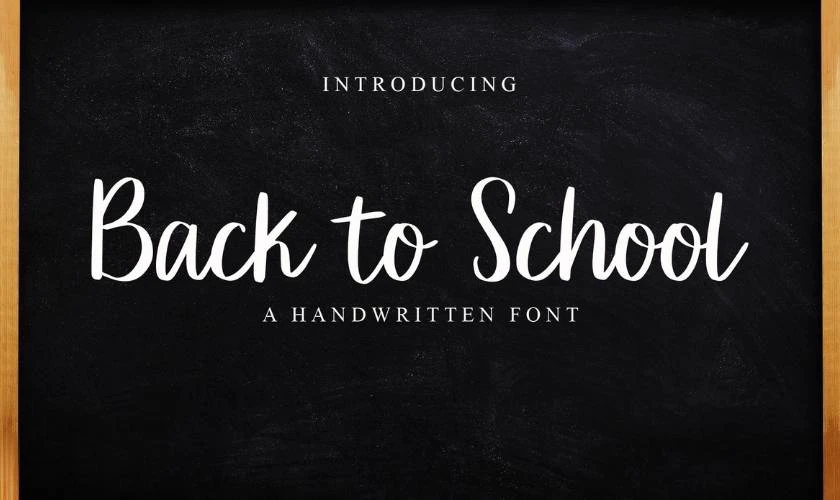
Nếu bạn muốn tìm một font mang hơi hướng retro và có tính học thuật hơn. CF Back to School là cái tên rất đáng cân nhắc. Nét chữ gọn, rõ, độ dày vừa phải giúp font này dễ dàng xuất hiện trên mọi thiết kế. Từ sách hướng dẫn, infographic lớp học cho đến thiệp mời khai giảng.
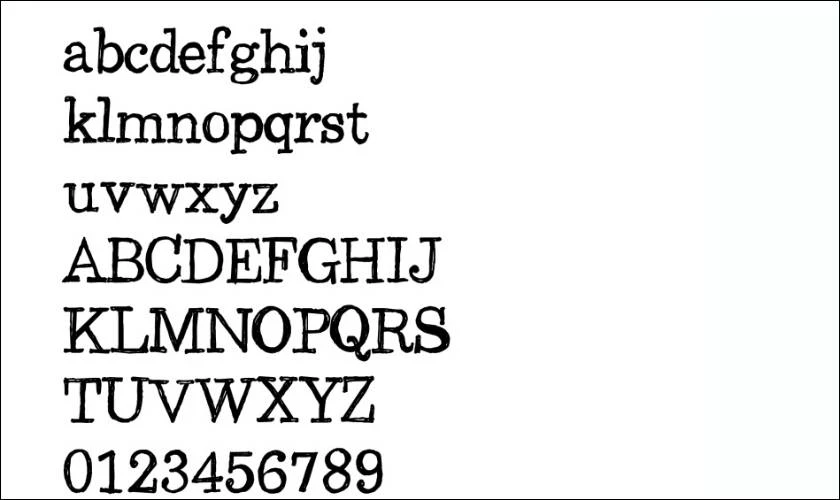
Không khí vui tươi, đáng yêu và dễ thương là điều mà font chữ PW mang đến. Nét chữ mềm mại, độ cong hài hòa khiến font này phù hợp với cấp mầm non, tiểu học. Nếu bạn đang làm sổ tay, bảng tên lớp hay thiệp handmade, font này là lựa chọn hoàn hảo.
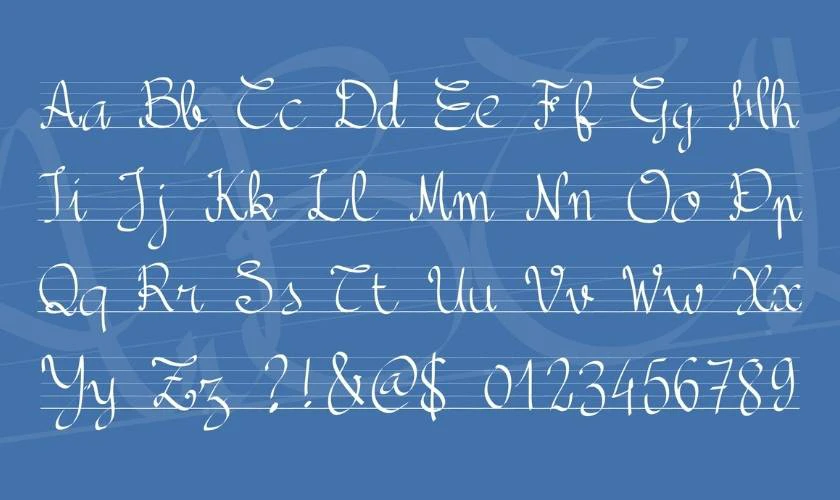
Imagex có kiểu dáng cổ điển nhưng vẫn giữ được tính hiện đại nhờ đường nét chắc khỏe, dứt khoát. Font chữ mùa tựu trường của Imagex thường được dùng cho tiêu đề lớn. Ví dụ như backdrop, banner hoặc áp phích sự kiện. Độ tương phản cao giúp font nổi bật mà vẫn giữ được sự chuyên nghiệp.
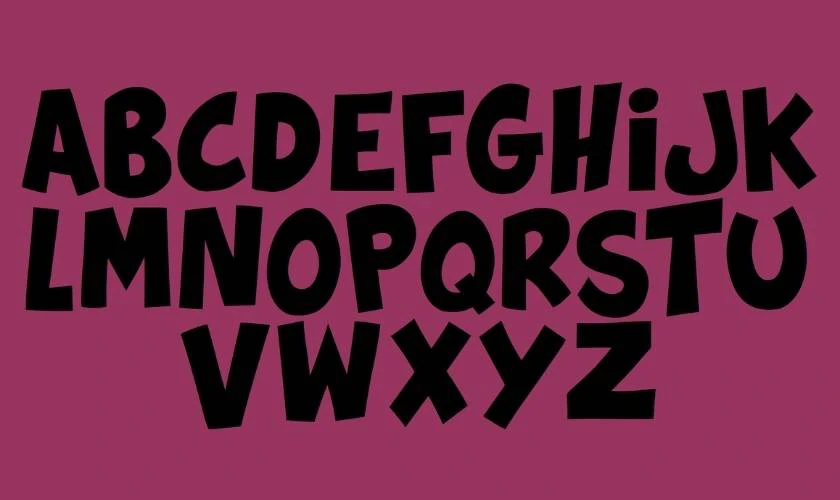
Đặc biết font khá “dễ tính” khi phối màu và dùng được cả trên nền tối lẫn nền sáng.
Phong cách tự do và có phần tinh nghịch. Đây là font rất được ưa chuộng trong các hoạt động ngoại khóa. Font này cực kỳ hợp cho các thiết kế mang tinh thần “nổi loạn nhẹ”. Chẳng hạn như áo lớp, sổ truyền thống hoặc poster sự kiện trường.
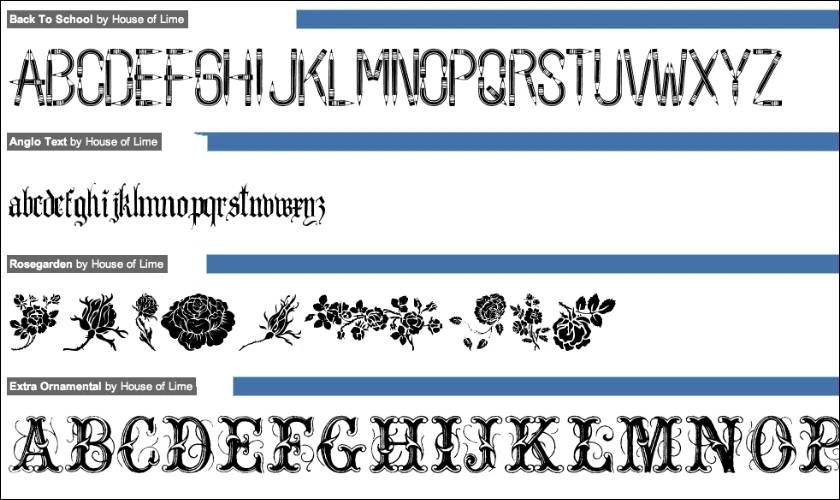
Dù có kiểu dáng hơi phá cách, House of Lime vẫn giữ được tính dễ đọc, rất thân thiện với người dùng. Bạn hoàn toàn có thể phối hợp font này cùng icon hoặc minh họa doodle để tăng phần sinh động.
School Mania là font mang phong cách học đường vui nhộn với các nét chữ đậm. Font dễ nhận diện, phù hợp với thiết kế cần sự nổi bật.
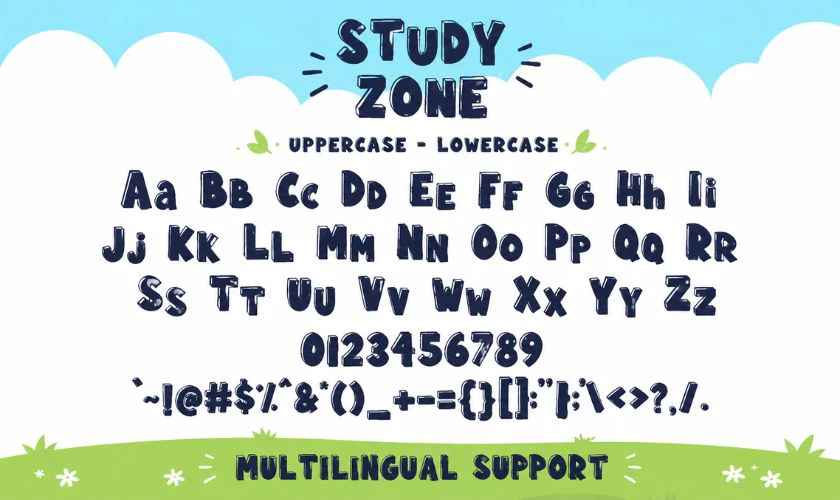
Bạn có thể dùng font này cho tiêu đề poster, banner khai giảng hoặc chương trình chào năm học mới. Font hoạt động tốt khi đặt ở vị trí trung tâm.
Sweetie Pie là font chữ viết tay với nét uốn lượn dịu dàng, thích hợp cho thiết kế dành cho học sinh nữ hoặc chủ đề trường học nhẹ nhàng, lãng mạn. Font có cả phiên bản thường và nghiêng.
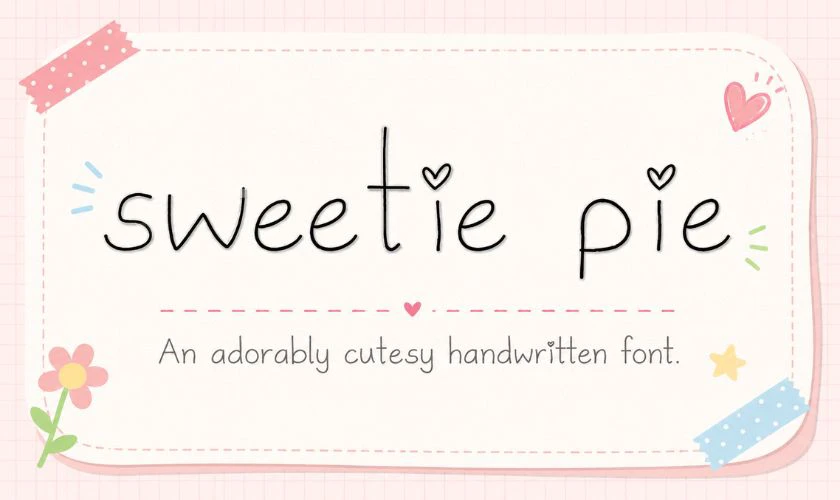
Màu sắc pastel kết hợp cùng Sweetie Pie sẽ cho ra bộ thiết kế hoàn chỉnh, phù hợp cho sticker vở bài tập, nhãn vở học sinh hay thẻ tên lớp học.
Pencil Pete mô phỏng nét vẽ bằng bút chì, tạo cảm giác rất gần gũi. Font gợi nhớ đến vở học sinh, bảng viết và các hoạt động lớp học.
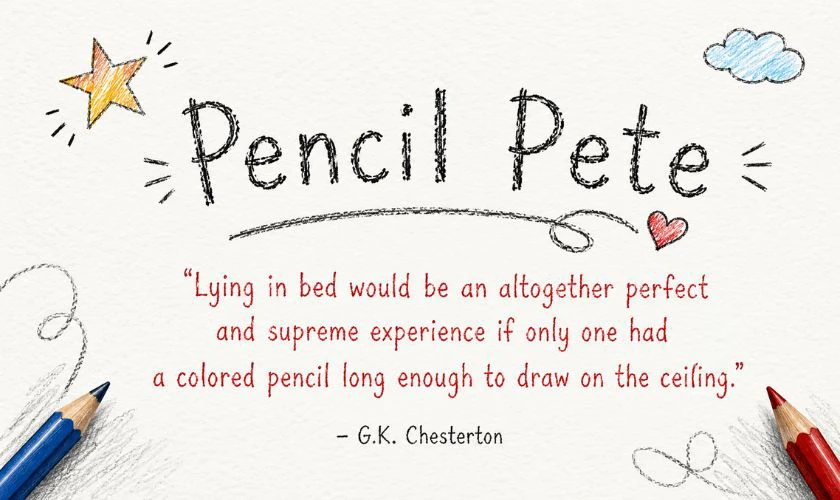
Đây là lựa chọn phù hợp cho thiết kế sáng tạo dành cho học sinh. Bạn có thể dùng Pencil Pete cho flashcard, poster học tập hoặc ảnh minh họa giáo dục.
School Days có phong cách trẻ trung, thân thiện và dễ đọc. Font phù hợp với nhiều nội dung học đường, từ thông báo đến bài đăng chào năm học.
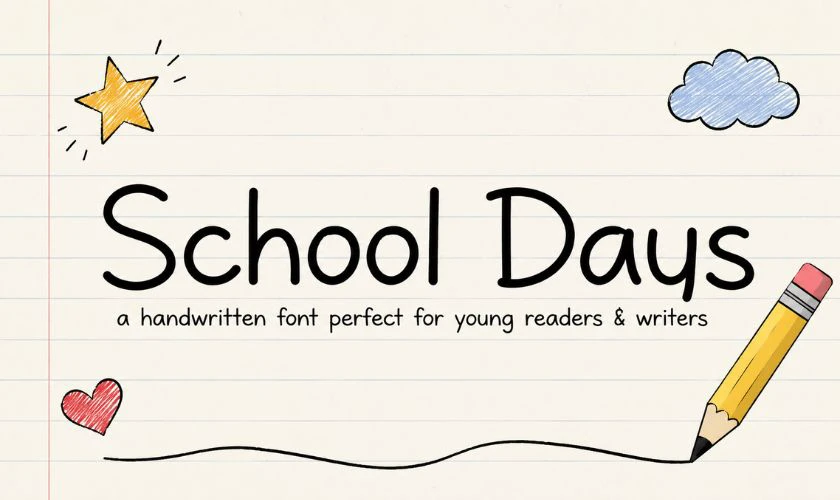
Font thường được dùng trong poster sự kiện, bảng thông báo hoặc tài liệu giới thiệu khóa học. Khi phối, nên chọn màu chữ rõ để tăng độ dễ nhìn.
Blackboard Font lấy cảm hứng từ chữ viết trên bảng đen. Font mang đậm không khí lớp học truyền thống và tạo cảm giác quen thuộc.
Bạn có thể dùng Blackboard Font cho banner, infographic giáo dục hoặc ấn phẩm mùa tựu trường. Font phù hợp với nền bảng đen, phấn trắng hoặc phong cách vintage.
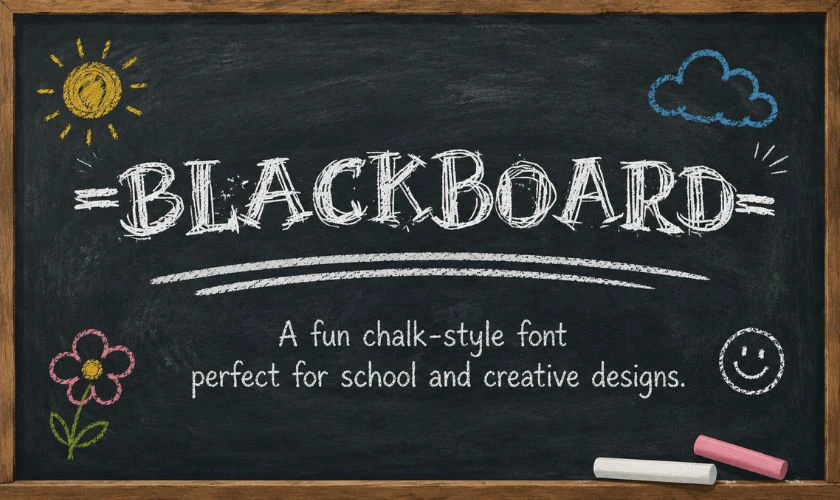
Nhìn chung, các font chữ trên đều mang đậm tinh thần học đường và có thể ứng dụng linh hoạt trong nhiều loại thiết kế khác nhau. Tùy theo phong cách mong muốn, bạn có thể lựa chọn font vui nhộn, sáng tạo hoặc mang hơi hướng lớp học truyền thống để tạo điểm nhấn cho các ấn phẩm mùa tựu trường.
Back to school font Việt hóa giúp thiết kế tiếng Việt đẹp và ít lỗi dấu. Đây là nhóm font nên ưu tiên khi làm nội dung cho website, fanpage hoặc poster.